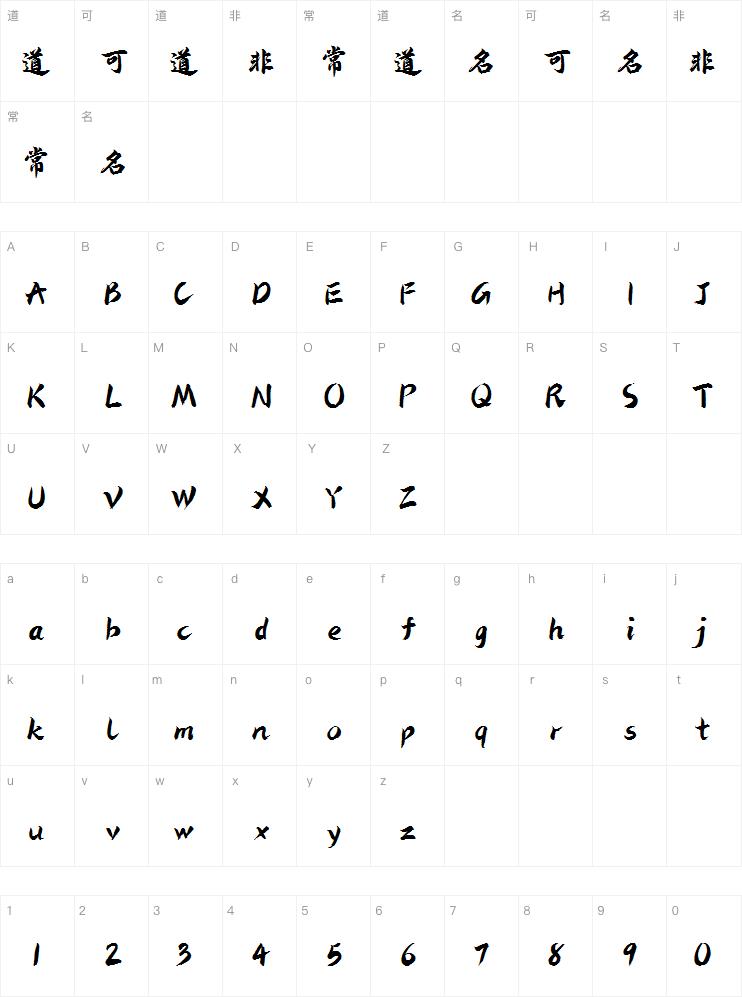
字魂仙剑奇侠体
字魂仙剑奇侠
"字魂仙剑奇侠体是一款有着流畅的书写感的字体,整套字体书写时运用了许多连笔技巧,不仅看起来行云流水、仙气缥缈,更是让字体体现出故事般“起承转合”的节奏。如整字书写时的一-气呵成;笔画转折时的游丝连横;部件闭合处的温婉衔接;笔断意连的地方更是留白巧妙。该字体适用于文化宣传等场景。"
字魂仙剑奇侠体